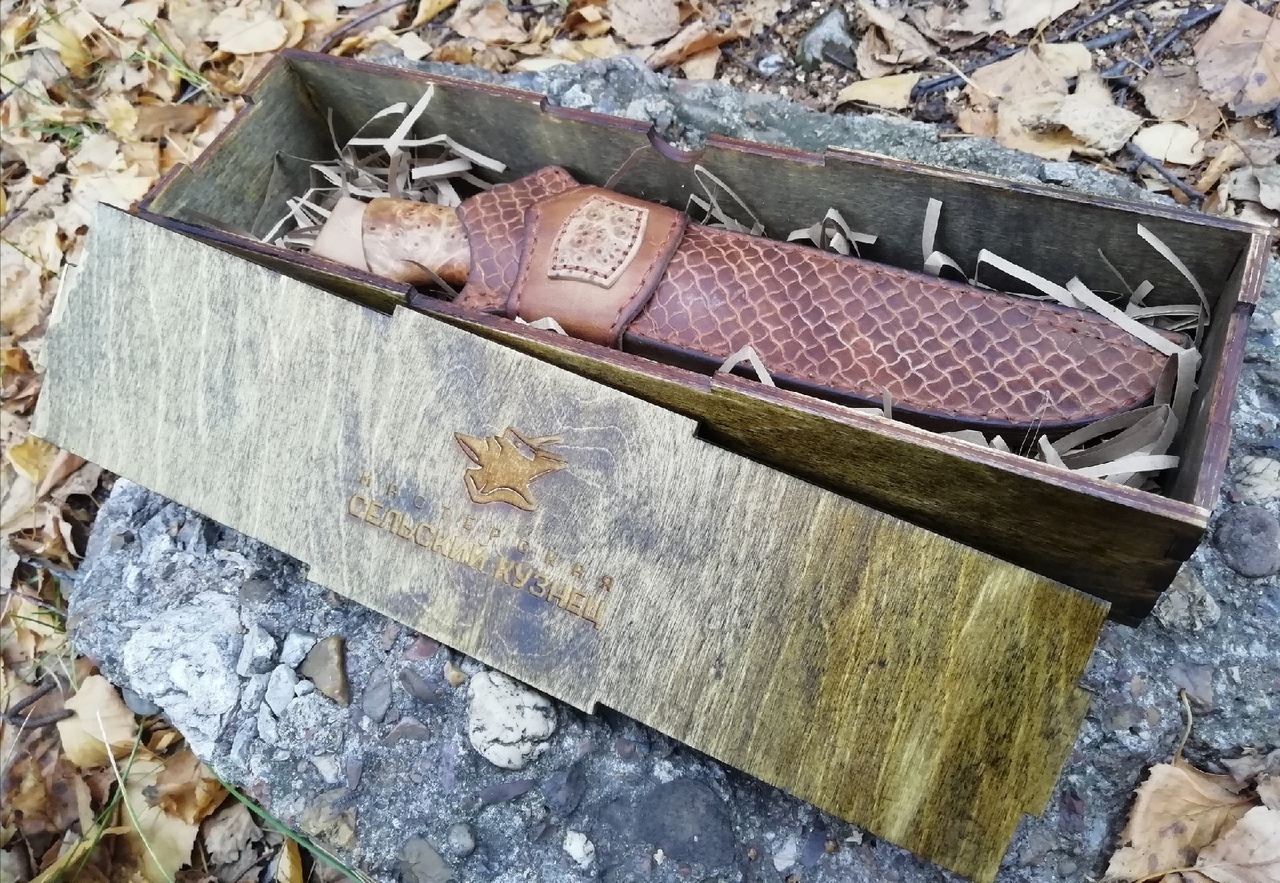
Geleneksel ahşap oyma işçiliğinden ilham alan bu dekoratif Kiril yazı tipi, rustik ve otantik projelerinize doğal bir hava katar. Logo tasarımları, ambalajlar ve el yapımı ürün etiketleri için mükemmel bir seçimdir.
Rustik Kiril Yazı Tipi - El Yapımı Tasarımlar İçin